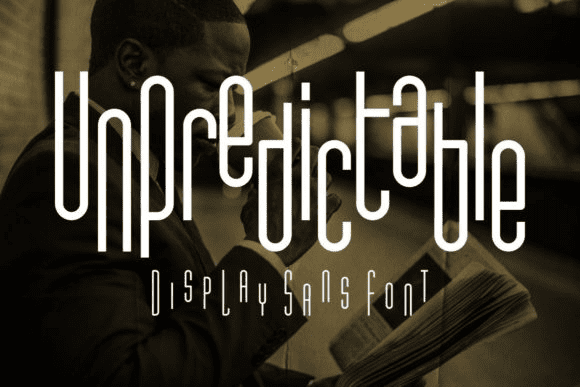
Непредсказуемый - это прохладный, высокий и тонкий без засечек шрифт.
Его легко подогнать под невероятно большой набор проектов, так что добавьте его к вашим творческим идеям и заметьте, как он выделяет их!